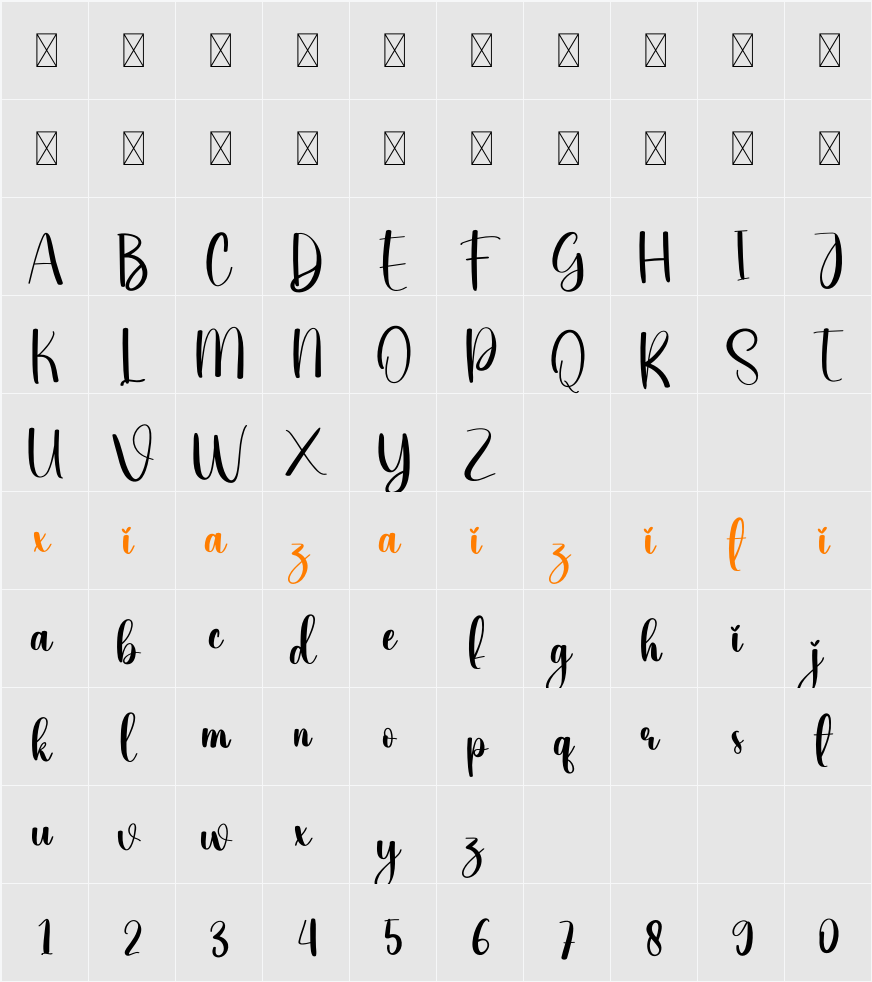
Write
Write,这款字体结构工整、笔画清晰,兼顾美观与易读性,适用于标题、正文、海报、包装、LOGO 等多种场景。字形优雅稳定,风格百搭耐看,适配日常排版与创意设计,让文字呈现更舒适、更具质感。Write一笔一画,皆是细节,以均衡的比例、流畅的线条打造舒适视觉体验,字形端正大气,风格简约现代。无论是商业设计、品牌宣传还是日常排版,都能轻松驾驭,让文字更有格调与力量。Write字体下载。